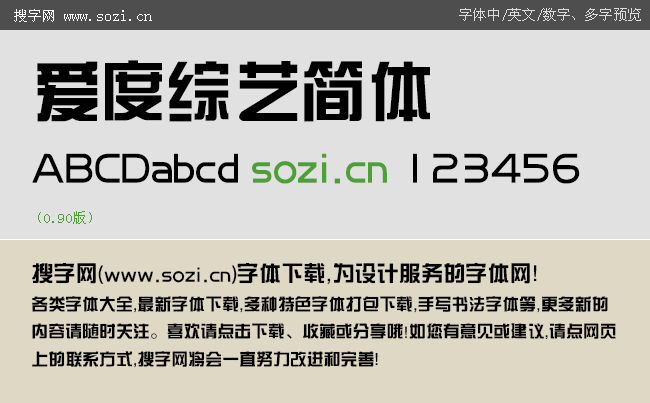
愛(ài)度綜藝簡(jiǎn)體
搜字網(wǎng)提供一款?lèi)?ài)度綜藝簡(jiǎn)體下載。綜藝體是黑體的一種變體,也是藝術(shù)字的一種。特點(diǎn)是筆劃更粗,盡量將空間充滿(mǎn)。同時(shí)為了美觀,對(duì)拐彎處的處理較為圓潤(rùn)。適用于廣告、報(bào)刊等的標(biāo)題及海報(bào)展板等設(shè)計(jì)場(chǎng)合使用。